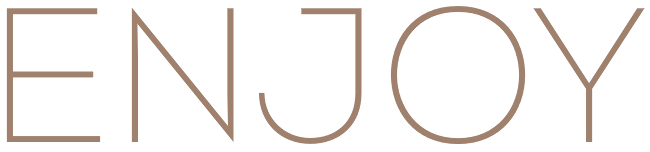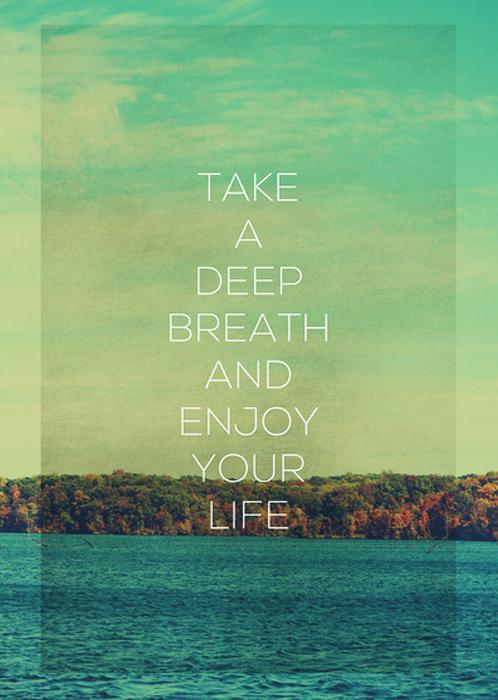
Nox Regular mit händischem "J" oder eigenständiger Font?
Leider werde ich nicht fündig.
Ich dachte es ist die Nox Regular aber der Letter "J" passt nicht.
Kennt jemand den Font auf der Grafik?